آموزش گام به گام اضافه کردن فونت به اینشات
اگر میخواهید افزودن فونت در اینشات را یاد بگیرید، در ادامه مقاله آموزش اضافه کردن فونت فارسی برای اینشات همراه ما باشید. در اینجا آموزش اضافه کردن فونت دلخواه به برنامه اینشات را آموزش میدهیم.
شخصی که کاربر معمولی برنامه Inshot است، میتواند متوجه شود که شما ویدیوی خود را در Inshot ویرایش کرده اید. استفاده از فونت جدید نه تنها متن را متمایز میکند، بلکه میتواند زیباتر هم به نظر برسد. برای مثال، اگر ویدیوی شما دارای تم قدیمی است، میتوانید یک فونت با سبک قدیمی مانند فونت ماشین تحریر را نصب و استفاده کنید. یک فونت منحصر به فرد خوب باعث میشود ویدیوی شما جذاب تر و حرفه ای تر به نظر برسد. حالا که متقاعد شدید، بیایید به نحوه اضافه کردن فونت به اینشات در گوشی بپردازیم.
آموزش اضافه کردن فونت دلخواه به برنامه اینشات
چرا باید فونتهای جدیدی را در برنامه Inshot نصب کنید وقتی از قبل مجموعه ای از فونتها در دسترس است؟ زیرا همه کسانی که از Inshot برای ویرایش فیلمها و عکسهای خود استفاده میکنند، فونتهای یکسانی خواهند داشت.
منابع فونت رایگان
وب سایتهای زیادی وجود دارند که فونتهای رایگان ارائه میدهند که میتوانید آنها را دانلود کنید. فونتها میتوانند از دستههای مختلفی مانند دست نویس، سریف، سان سریف، رومی، کمیک و غیره باشند. در اینجا لیستی از سایتهایی وجود دارد که مجموعه خوبی از فونتها را دارند:
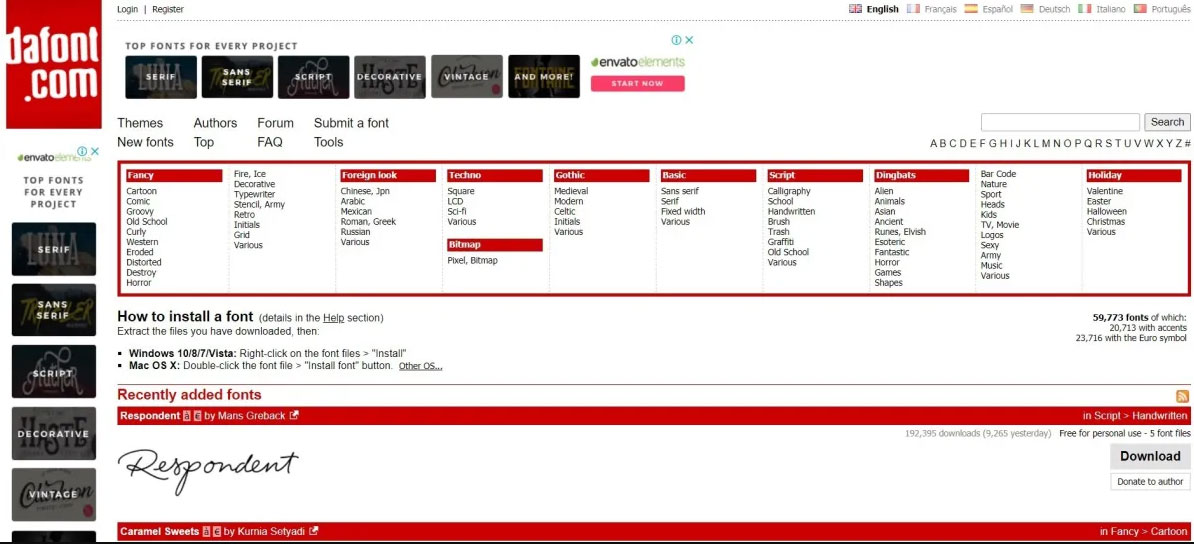
برای دانلود فونت فارسی برای اینشات اندروید هم میتوانید از سایتهای فونت فارسی استفاده کنید.
وقتی فونتهایی را از هر یک از سایتهای فهرست شده در بالا دانلود میکنید، یا حتی آنهایی که در این پست فهرست نشدهاند، یک پوشه زیپ دانلود میشود. این پوشه zip حاوی فایلهای نصب فونت است.
به مدیر فایل تلفن خود > دانلودها بروید و پوشه zip را انتخاب کرده و آن را از حالت فشرده خارج کنید. فایلهای فونت در یک پوشه استخراج میشوند.
اضافه کردن فونت برای اینشات اندروید و آیفون
Inshot را باز کنید و صفحه ویرایش یک ویدیو یا عکس را باز کنید. یک متن را تایپ کنید و به گزینه انتخاب فونت بروید.
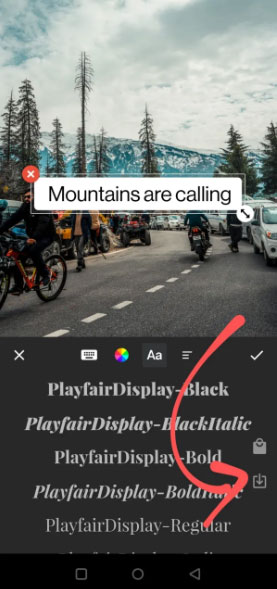
اگر فونتی را که دانلود کرده اید در این صفحه نمیبینید، روی Directories در پایین کلیک کنید تا به پوشه Downloads بروید. بسیار مهم است که پس از دانلود، برای اضافه کردن فونت برای اینشات ایفون پوشه را از حالت فشرده خارج کنید وگرنه فونت در برنامه نمایش داده نمیشود.
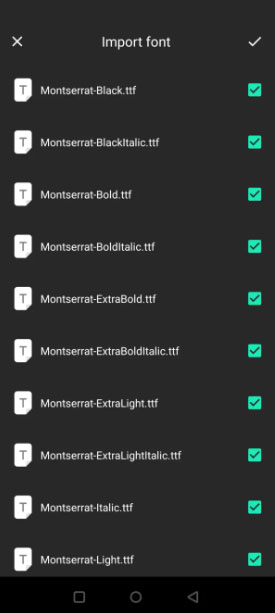
پس از انتخاب فونت مورد نظر، میبینید که اضافه کردن فونت به اینشات در ایفون انجام شده است.